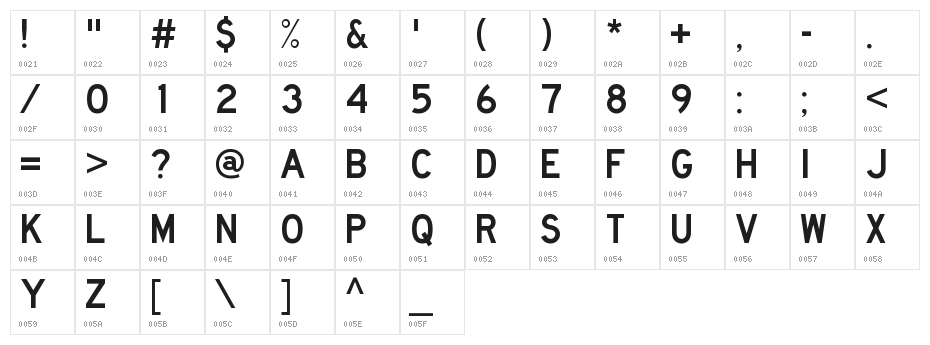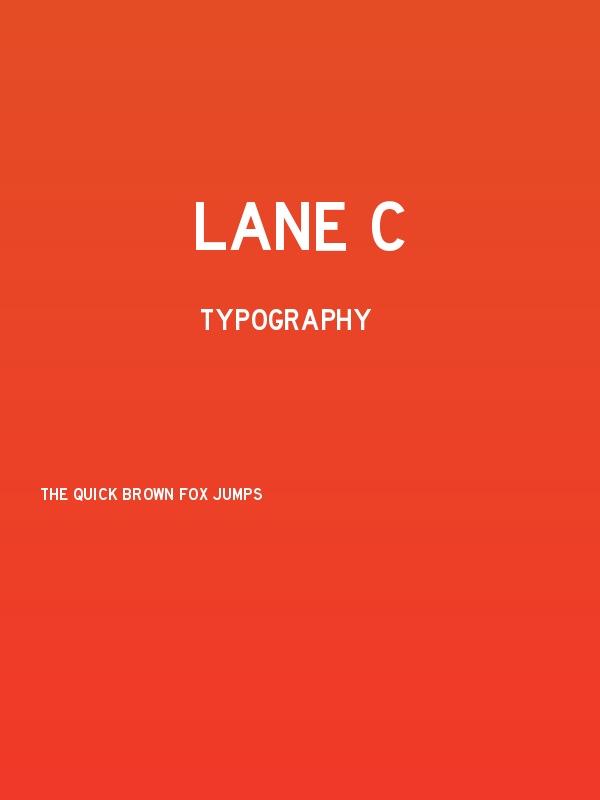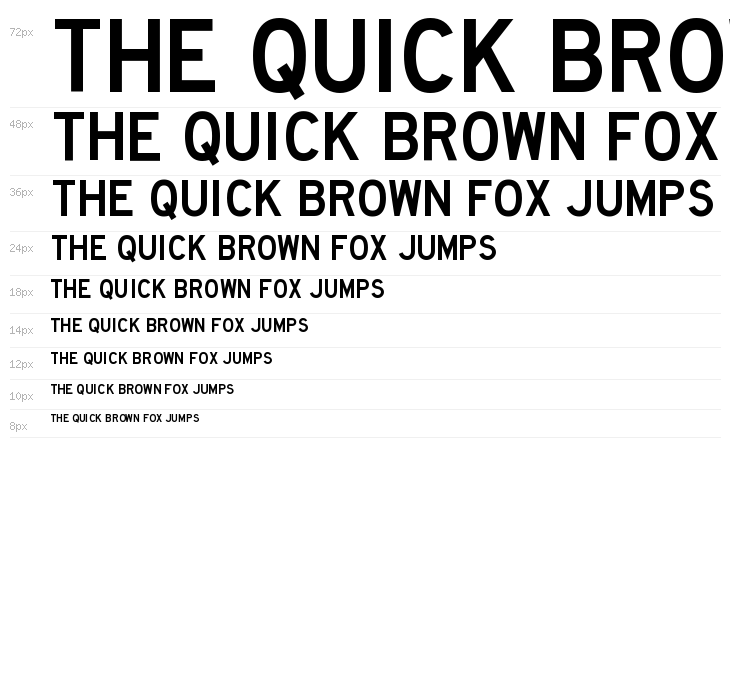
Lane C Font
✎ Capitals
| Anwendungsfall | Headlines, Logos, Digital Interfaces |
| Vorgeschlagene Projekte | Ideal for branding, signage, digital interfaces, and editorial design due to its clarity and modern appeal. |